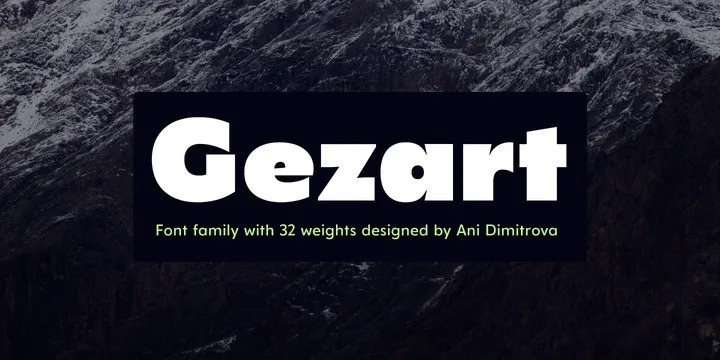
Gezart Sans Serif Font Demo – Fonte Grátis
Gezart Sans Serif Font Demo
Introduzimos a Gezart Sans Serif Font, uma tipografia sans-serif moderna com uma pegada geométrica. Desenvolvida pela designer Ani Dimitrova, esta família de fontes apresenta um total de 32 pesos: 16 tipos rectos e seus correspondentes itálicos. Os pesos vão desde Fininho até Pesado, com um deles (Extra Thin) disponível gratuitamente. A Gezart é uma tipografia perfeitamente adaptada para várias áreas de aplicação, incluindo design de marca, layouts digitais, texto do corpo, web design e design editorial. Ela vem equipada com recursos OpenType que permitem personalizar o tipo ainda mais. Estes incluem opções como minúsculas maiúsculas, formas localizadas, figuras de estilo antigo, ligaturas padrão, subescritos e superescritos, notações numéricas, símbolos circulares e moedas, além de frações. A Gezart é uma opção perfeita para quem procura um tipo elegante que não perde a personalidade moderna, ideal tanto para projetos de design editorial quanto para o layout web ou criação de materiais impressos. Seja você designer gráfico, editor de blogs ou simplesmente alguém interessado em recursos gráficos únicos e sofisticados, Gezart Sans Serif Font é uma excelente opção para suas necessidades.